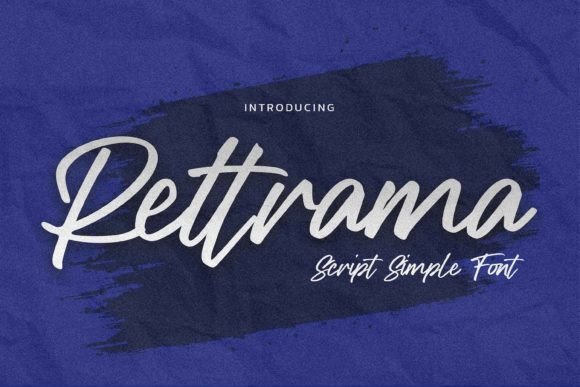
Rettrama
Если вы ищете высококачественные ресурсы, такие как Rettrama, этот премиум-пакет — фантастический выбор для ваших творческих проектов.
Создаете ли вы продукты POD (печать по требованию), свадебные приглашения или графику для социальных сетей, Rettrama станет идеальным выбором.